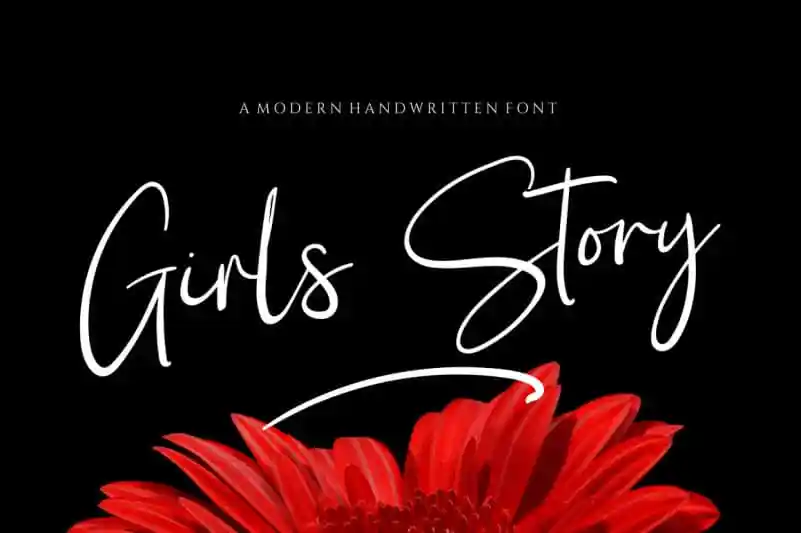
Girl Story Signature Script Font – Download Grátis
Girl Story Signature Script Font é uma elegante fonte de letra escrita à mão que transmite delicadeza e sofisticação. Seus caracteres distintos e redondos atraem atenção com facilidade, tornando-a perfeita para gráficos de alta qualidade. O fato de ser PUA (Propriedades Unicode Avançadas) permitido faz com que seja ainda mais especial: você pode acessar todas as gílias e swashes sem qualquer dificuldade. Instalar ou usar esta fonte implica que aceitou os Termos de Uso do Produto, garantindo que esteja em conformidade com os requisitos de uso estabelecidos. Girl Story Signature Script Font é uma escolha ideal para designers que buscam um toque delicado e sofisticado no seu próximo projeto visual.